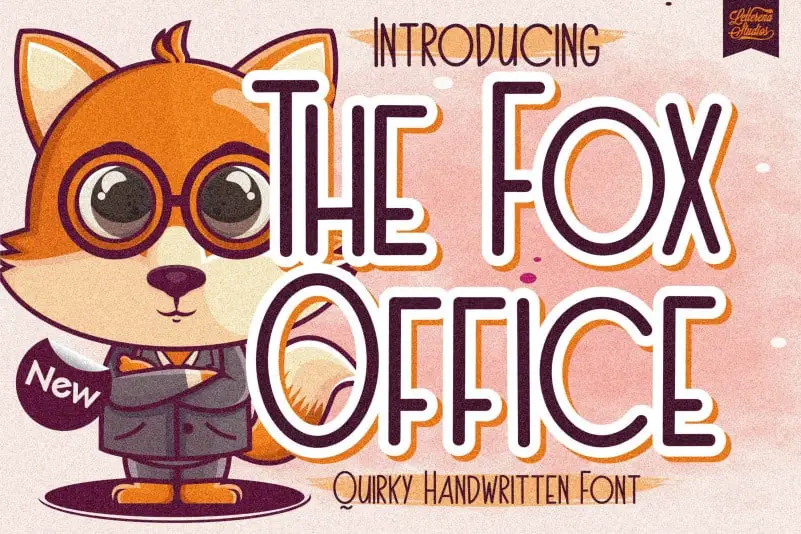
The Fox Office Display Font – Fonte Grátis
The Fox Office Display Font
A fonte “The Fox Office Display Font” oferece uma experiência única para designers e criadores de conteúdo, especialmente aqueles em busca de um visual natural e versátil. Ideal tanto para aplicativos como criações digitais quanto para impressão em grande escala, esta fonte é perfeita para qualquer projeto que exija estilo e presença no mundo do design. Com uma tipografia simples e elegante, sua altura sobressai naturalmente, tornando-a a escolha ideal para qualquer tipo de conteúdo. Perfeito para branding, embalagens de produtos, convites, citações, camisetas personalizadas ou qualquer mídia visual que você queira destacar. A letra do “Fox Office Display Font” é um recurso perfeito tanto online quanto offline, garantindo um alto nível de qualidade e facilidade de uso em diversos ambientes. Essa fonte destaca-se pelo seu equilíbrio entre simplicidade e poder visual, tornando-a a escolha ideal para designers atemporais que valorizam uma aparência natural e confortável. Adoptar o “Fox Office Display Font” é como adicionar um toque de natureza e eficácia ao seu design. Seja você um estilista de moda criando roupas personalizadas, um designer gráfico em busca de um fonte atraente para trabalhos digitais ou até mesmo um artesão desenhando sua própria etiqueta para sua loja, esta fonte está sempre pronta para ajudar você a alcançar seu objetivo visual.